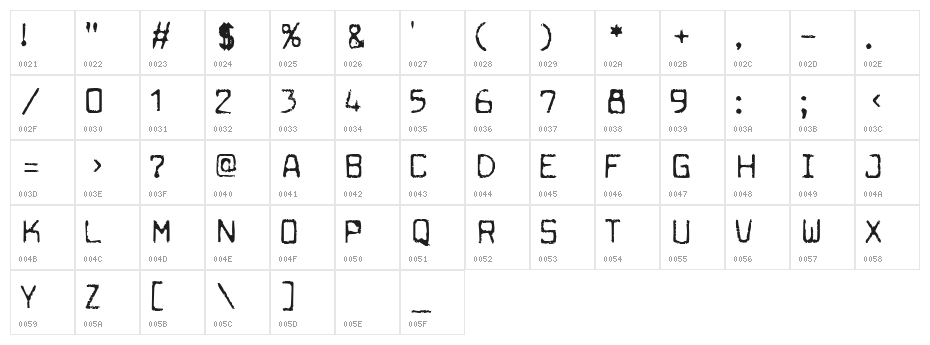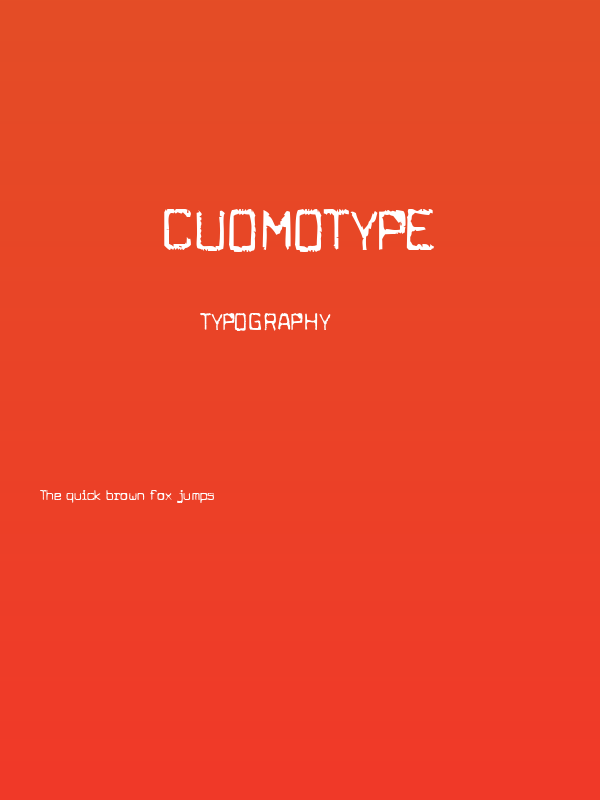
Cuomotype Font
| Stile generale | Grunge, Distressed |
| Progetti proposti | Ideal for album covers, posters, branding for edgy or alternative products, and any design needing a bold, gritty look. |